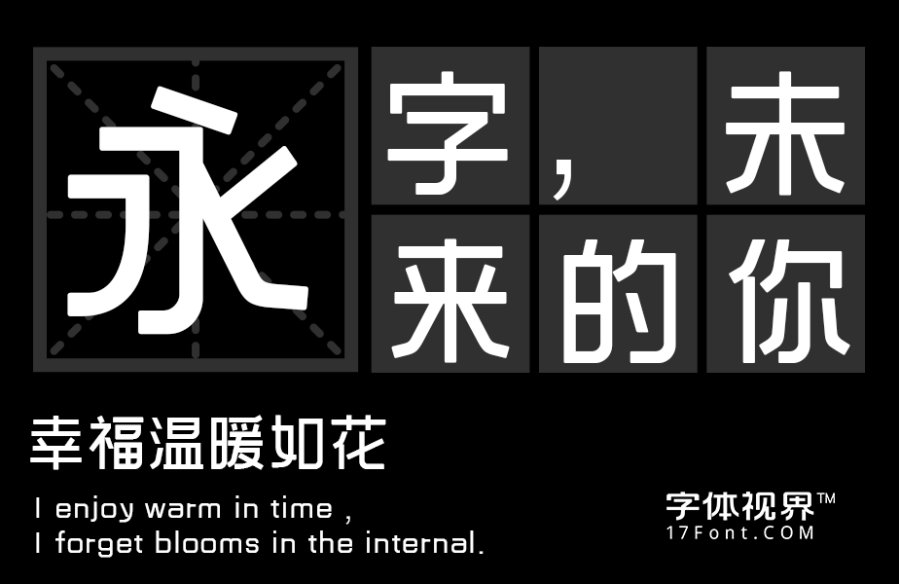
三极信黑简体发布
字体名称:三极信黑简体
字体类别: 创意字体、黑体
适用场景:标题、LOGO、印刷、屏显
三极信黑简体简介:三极信黑简体是是一款几何感十足的创意字体。其笔画多以对称的手法来表现,撇、捺都有明显的几何转折,不同于书写状态的连续弧线。起笔收笔都为圆角,字体更加精致,使字体刚中带柔。使用了大弧度笔画加强了字体特有的视觉个性。适用于书刊封面、广告品牌、产品包装设计等。
三极信黑简体预览图展示: